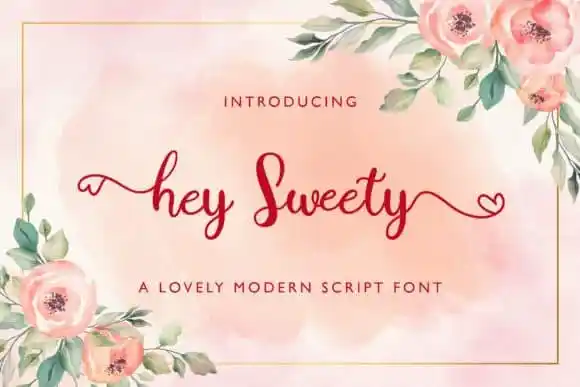
Hey Sweety Calligraphy Font
Aqui está uma breve descrição para a página de download da fonte ‘Hey Sweety Calligraphy Font’: Introduzimos Hey Sweety Calligraphy Font – uma tipografia criada à mão que oferece formas modernas e únicas do caligrafismo. Esta criação do designer StringLabs transmite um estilo natural na escrita, tornando-a ideal para diversas aplicações, desde cartões de agradecimento e convites de casamento até logomarcas e cartões de negócios. O nome “Hey Sweety” não é apenas uma referência ao design encantador da fonte, mas também sugere um toque suave e aconchegante – o que certamente irá deixar seu projeto em evidência. Essa font se destaca especialmente nos momentos delicados de celebração ou apreciação, como cartões de casamento ou convites de aniversário, onde uma escrita à mão convida um ar pessoal e emocionalmente significativo. Sua elegância e charme fazem com que Hey Sweety seja perfeitamente adequada para qualquer design que precise de uma pitada de escrita à mão. Não importa o projeto; esta fonte certamente fará dele um destaque visual e emocionante.